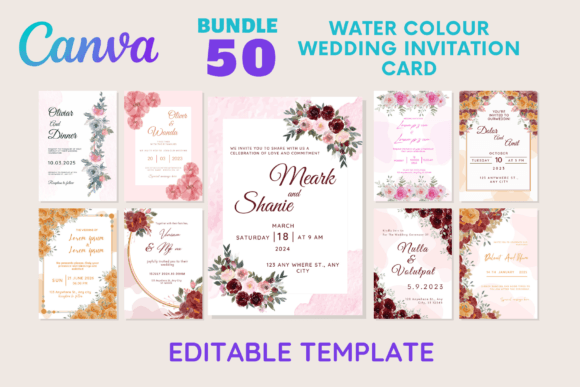
Water Colour Wedding Invitation Card
Mencari elemen reka bentuk yang sesuai boleh menjadi mencabar, tetapi Water Colour Wedding Invitation Card menawarkan koleksi luar biasa yang menaik taraf karya anda serta-merta.
Sama ada anda mencipta produk POD (Print on Demand), jemputan perkahwinan atau grafik media sosial, Water Colour Wedding Invitation Card amat bersesuaian.